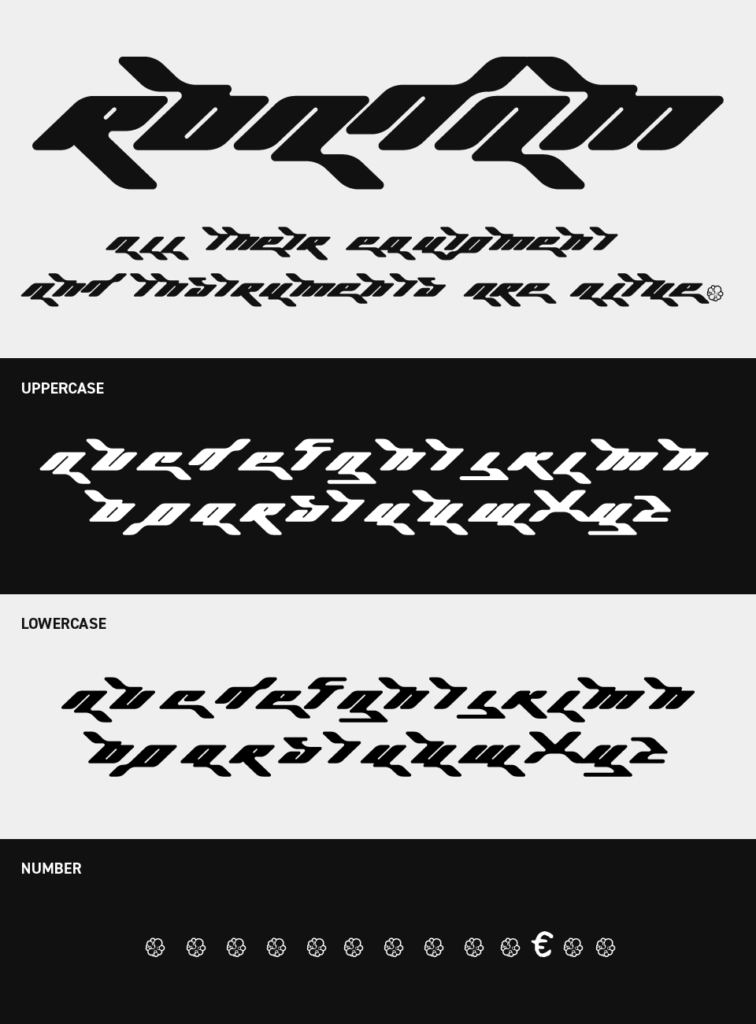
Roadam Font
Roadamフォントは、スピード感あふれる斜め構成と鋭いエッジが印象的な、レーシングテイストのデザインフォントです。
文字全体が前方へ加速しているようなシルエットで、見るだけで勢いが伝わります。スポーツやモーターテイストのデザインにぴったりで、スピード感を表現できるちょっぴり攻めているフォントです。
メカニカルっぽさのある近未来的な雰囲気がとってもステキです。ゲームロゴ、eスポーツ、車関連ブランド、エナジー系ビジュアルなど、瞬発力や躍動感を打ち出したい場面でぴったりです。